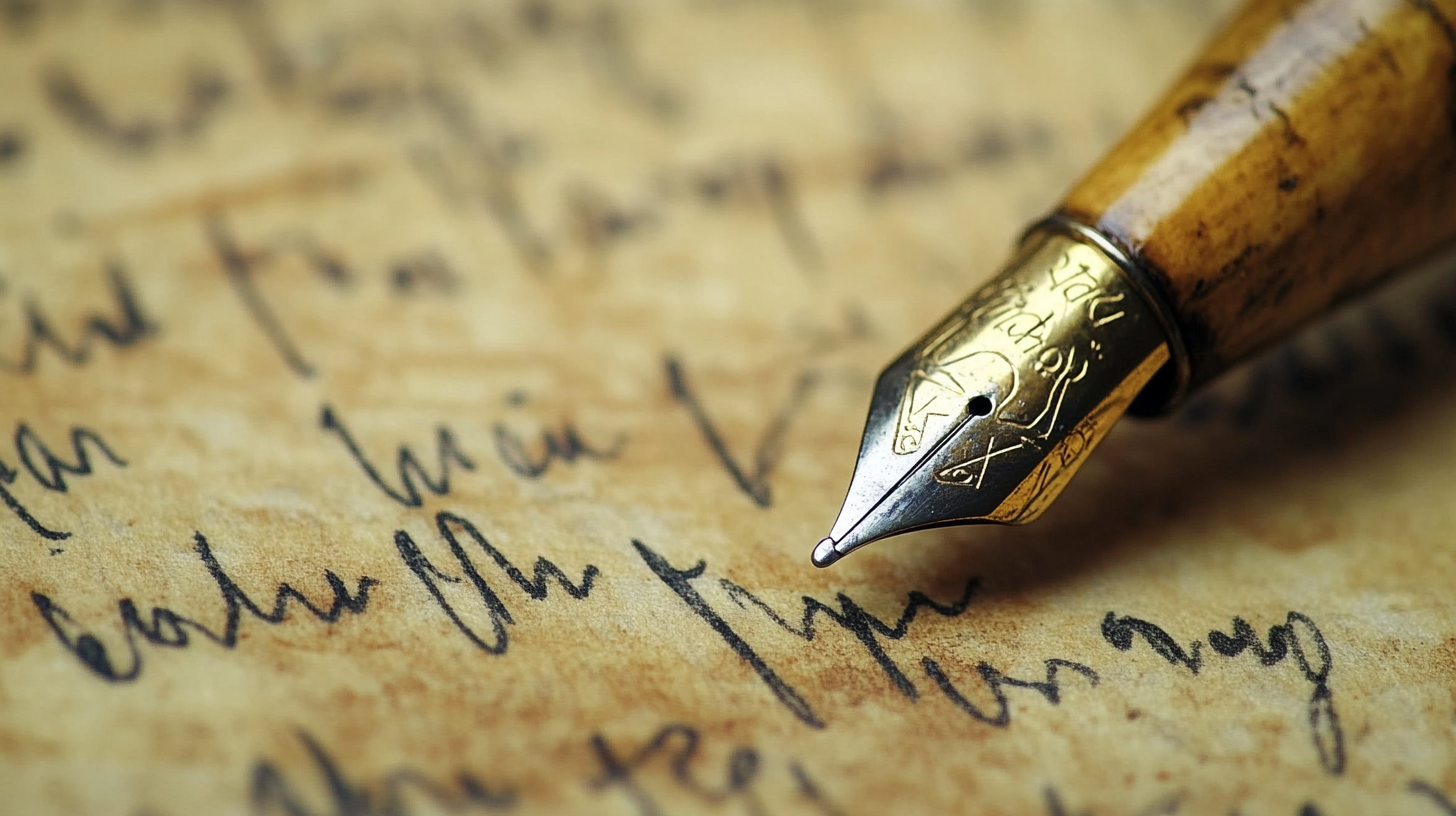
"글씨 교정, 최소 몇 개월은 걸리겠지?" 아니요! 단 3일 만에 눈에 띄는 변화를 경험할 수 있어요! 🚀 글씨 교정의 핵심은 정확한 연습법과 집중력이에요. 이번 훈련법을 따라 하면 3일 후 훨씬 깔끔해진 글씨체를 만날 수 있을 거예요. ✍
오늘은 하루 30분씩 3일 동안 집중적으로 연습할 수 있는 효과적인 글씨 교정 훈련법을 알려드릴게요! 😊
📝 1일 차 - 기본 획과 글씨 구조 익히기
첫째 날에는 글씨 교정의 기초가 되는 획의 정리와 글씨 구조 익히기를 연습할 거예요. ✍ 획이 흐트러지면 글씨체가 고르지 않고 읽기 어려워지기 때문에 처음에는 획을 정리하는 것이 가장 중요해요! 😊
이날 연습할 핵심 포인트는 ✅ 올바른 필기 자세 ✅ 직선, 곡선, 대각선 기본 획 연습 ✅ 글자 크기와 간격 맞추기 이 3가지예요! 🚀
📌 1일 차 훈련 계획
시간 연습 내용 목표 10분 올바른 필기 자세 유지 & 손 스트레칭 손의 긴장을 풀고 편안한 필기 습관 형성 10분 직선, 곡선, 대각선 기본 획 연습 획이 균일하고 반듯하게 정리되도록 연습 10분 글자 크기와 간격 맞추기 (모눈 노트 활용) 균형 잡힌 글씨체 연습 연습을 마친 후, 오늘 연습한 획과 글씨를 비교하면서 어떤 부분이 부족한지 체크해보세요! 😊 이제 2일 차 - 자간과 행간 조절 연습을 시작해볼까요? ✨
📏 2일 차 - 자간과 행간 조절 연습
둘째 날에는 자간(글자 사이 간격)과 행간(줄 간격) 맞추기 연습을 해볼 거예요. ✍ 자간과 행간이 일정하지 않으면 글씨가 엉성해 보이고 읽기 어려워질 수 있어요. 하지만 작은 습관만 바꿔도 훨씬 정돈된 글씨체를 만들 수 있답니다! 😊
이날 연습할 핵심 포인트는 ✅ 글자 사이 간격을 균일하게 맞추기 ✅ 줄 간격을 일정하게 유지하는 방법 ✅ 모눈 종이 & 가이드라인 활용하기 이 3가지예요! 🚀
📌 2일 차 훈련 계획
시간 연습 내용 목표 10분 자간 맞추기 연습 (모눈 종이 활용) 글자 간격을 균등하게 조절하는 습관 형성 10분 행간 일정하게 유지하며 문장 쓰기 깔끔하고 정돈된 문장 필기 연습 10분 모눈 노트 없이 글씨 크기 & 간격 맞춰보기 자연스럽게 균형 잡힌 필체 완성 연습을 마친 후, 오늘 쓴 글씨를 1일 차 연습과 비교해보세요! 😊 자간과 행간이 정돈되었는지 체크해보는 것이 중요해요. 이제 3일 차 - 필기 속도와 실전 필사를 연습해볼까요? ✨
⚡ 3일 차 - 필기 속도와 실전 필사
마지막 날에는 속도 조절과 실전 필사 연습을 진행할 거예요. ✍ 아무리 정갈한 글씨라도 필기 속도가 너무 느리면 실용성이 떨어질 수 있어요. 그래서 정확하면서도 빠르게 필기하는 연습이 필요하답니다! 😊
이날 연습할 핵심 포인트는 ✅ 일정한 속도로 글씨 쓰는 연습 ✅ 필사를 통해 자연스럽게 글씨체 다듬기 ✅ 실전에서 활용할 수 있도록 필기 실습하기 이 3가지예요! 🚀
📌 3일 차 훈련 계획
시간 연습 내용 목표 10분 일정한 속도로 단어 연습 (타이머 활용) 필기 속도를 일정하게 유지하는 습관 형성 10분 좋아하는 문장 필사 연습 자연스럽고 부드러운 필체 익히기 10분 실전 필기 (노트 필기, 일기 쓰기) 실제 상황에서도 깔끔한 글씨체 유지 3일 동안의 훈련이 끝났어요! 🎉 이제 처음과 비교했을 때 글씨체가 얼마나 달라졌는지 확인해보세요. 하지만 꾸준한 연습이 없다면 다시 원래 습관으로 돌아갈 수도 있어요. 그렇다면, 효과를 극대화하는 연습 루틴을 알아볼까요? 🤔
🚀 효과를 극대화하는 연습 루틴
3일 동안 연습한 내용을 꾸준히 유지하려면 일정한 루틴을 만드는 것이 중요해요! ✍ 짧은 시간이라도 매일 연습하면 손글씨가 점점 더 정리되고 자연스러운 필체를 가질 수 있어요. 😊
이 루틴을 따라 하면 하루 15분 투자로도 충분히 글씨 교정 효과를 극대화할 수 있어요! 🚀
📌 하루 15분 글씨 교정 루틴
시간 연습 내용 효과 5분 기본 획 & 자간 연습 획의 균형 잡기 & 글자 정렬 개선 5분 짧은 문장 필사 손글씨 흐름과 자연스러움 익히기 5분 실전 필기 (노트 정리, 일기 쓰기 등) 실제 상황에서도 깔끔한 글씨 유지 이 루틴을 최소 2~4주 동안 꾸준히 실천하면 글씨체가 훨씬 예쁘고 정돈된 느낌으로 바뀔 거예요! ✨ 그렇다면, 이런 연습을 도와줄 필수 도구에는 어떤 것들이 있을까요? 🤔
🛠 필수 도구 추천
글씨 교정을 할 때는 올바른 도구를 사용하는 것도 매우 중요해요! ✍ 필기구와 노트 종류에 따라 획의 정리, 필압 조절, 글자 크기 조절이 훨씬 쉬워질 수 있답니다. 😊
여기, 글씨 교정에 꼭 필요한 필수템을 정리해봤어요! 이 도구들을 활용하면 더욱 효과적으로 글씨를 연습할 수 있을 거예요. 🚀
📌 글씨 교정에 도움이 되는 필수 도구
도구 추천 이유 ✏ 2B 연필 필압 조절이 쉽고, 수정이 가능해서 초보자에게 적합 🖊 유성 볼펜 (0.5mm) 획이 선명하게 유지되어 실전 필기 연습에 적합 📖 모눈 노트 글자 크기와 자간을 일정하게 유지하는 데 도움 📏 글씨 교정 워크북 올바른 획과 글씨 구조를 익히는 데 효과적 🖋 만년필 (초보용 EF촉) 획의 흐름을 부드럽게 익힐 수 있음 ⌛ 타이머 정해진 시간 내에 연습할 수 있도록 도와줌 이 도구들을 활용하면 훨씬 더 효율적으로 글씨를 교정할 수 있어요! 😊 하지만, 꾸준함이 가장 중요하다는 점! 그렇다면 글씨 교정을 꾸준히 연습하는 팁에는 어떤 것들이 있을까요? 🤔
💡 꾸준히 연습하는 팁
글씨 교정에서 가장 중요한 것은 꾸준함이에요! ✍ 하지만 연습을 계속하기란 쉽지 않죠. 😅 그래서 즐겁고 효과적으로 연습을 지속하는 팁을 소개해드릴게요! 😊
이 팁들을 활용하면 쉽게 포기하지 않고 글씨 교정을 습관처럼 만들 수 있을 거예요! 🚀
📌 꾸준히 글씨 연습하는 5가지 방법
팁 설명 🎯 목표 설정 한 달 후 목표 글씨체를 정하고 비교하기 📅 일정 만들기 하루 10~15분 정해진 시간에 연습하기 📝 다양한 필사 도전 좋아하는 책, 명언, 가사 등을 필사하기 📸 연습 과정 기록 연습 전후 사진을 찍어 변화를 눈으로 확인 💬 함께 연습하기 친구나 커뮤니티에서 함께 연습하며 동기 부여 위 방법들을 실천하면 더 즐겁게, 그리고 꾸준하게 글씨 연습을 할 수 있을 거예요! 😊 이제 글씨 교정과 관련된 자주 묻는 질문을 정리해볼까요? 🤔
Q1. 정말 3일 만에 글씨가 달라질 수 있나요?
A1. 네! ✨ 올바른 연습법을 따르면 3일 만에도 획이 정리되고 글씨체가 균형 잡히는 변화를 느낄 수 있어요. 하지만 완벽한 교정을 위해서는 꾸준한 연습이 필요해요. 😊
Q2. 하루에 몇 분씩 연습하는 것이 효과적인가요?
A2. 하루 10~15분 정도 꾸준히 연습하는 것이 좋아요. 짧은 시간이라도 매일 연습하면 손글씨 습관이 자연스럽게 개선될 수 있어요! ⏳
Q3. 글씨 교정할 때 어떤 필기구를 사용하는 게 가장 좋을까요?
A3. 초보자는 2B 연필을 추천해요! ✏ 획을 부드럽게 연습할 수 있고, 필압 조절이 쉬워서 초반 연습에 적합해요. 이후에는 유성 볼펜으로 실전 필기를 연습하는 것이 좋아요! 🖊
Q4. 악필이 너무 심한데 교정이 가능할까요?
A4. 네, 가능합니다! 😊 악필도 획 연습 → 글자 정렬 → 필사 연습 순서대로 체계적으로 교정하면 누구나 바른 글씨체를 가질 수 있어요.
Q5. 필사 연습을 할 때 어떤 글을 따라 쓰는 게 좋을까요?
A5. 좋아하는 책, 명언, 노래 가사 등을 필사해보세요! 📖 관심 있는 내용을 쓰면 더 재미있게 연습할 수 있고, 연습 과정도 덜 지루하게 느껴질 거예요. 😊
Q6. 글씨 교정을 하면서 가장 중요한 것은 무엇인가요?
A6. 균형과 꾸준함! ✍ 획을 균형 있게 정리하고, 매일 조금씩 연습하는 것이 가장 중요해요. 꾸준히 연습하면 반드시 변화가 생길 거예요! 🚀
Q7. 필기 속도를 높이면서도 글씨를 깔끔하게 쓰는 방법이 있나요?
A7. 네! ⏳ 처음에는 천천히 정확하게 쓰는 연습을 하면서 점점 속도를 올리는 것이 좋아요. 또한, 펜의 흐름을 부드럽게 유지하는 연습도 효과적이에요!
Q8. 연습한 글씨체가 다시 원래대로 돌아가지는 않을까요?
A8. 그래서 꾸준한 연습이 중요해요! 😊 최소 한 달 정도 글씨 연습을 유지하면 손이 새로운 글씨 습관에 적응하게 돼요. 이후에는 자연스럽게 예쁜 글씨체가 유지될 거예요! ✨
이제 글씨 교정에 대한 모든 궁금증이 해결되었나요? 😊 오늘부터 3일 동안 집중 훈련을 해보세요! 변화된 글씨체를 보며 뿌듯함을 느끼실 거예요! ✨